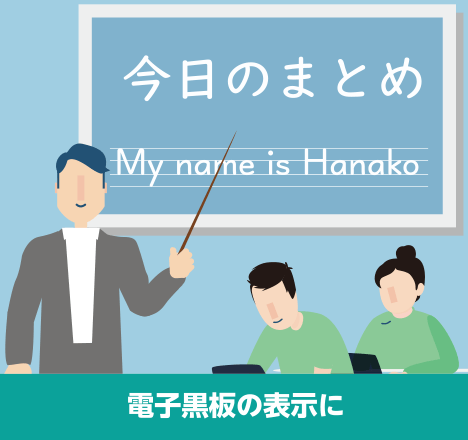
「MORISAWA BIZ+」は、教育現場のあらゆるドキュメントやコンテンツの作成に、多くの人々が利用しやすいユニバーサルデザイン(UD)フォントの利用を提案する新しいサービスです。
UDデジタル教科書体の特徴
一般的な教科書
筆書きの楷書に近く、線の太さに強弱があり見えにくい
ゴシック体
教育現場に準じた字形ではないため、運筆の方向がわかりにくく教えにくい
UDデジタル教科書体
ロービジョン(弱視)やディスレクシア(読み書き障害)に配慮したデザイン学習指導要領に準拠した字形。
電子黒板やタブレットの表示などICT教育で効果を発揮
より良い学びに適した字形に
- 運筆の向きがわかるように字形を工夫
- 同じ部首や同系列の構成要素を持つ漢字字形をルール化
MORISAWA BIZ+収録フォント
- 一般的なフォント
- BIZ UDフォント
文字のかたちが
わかりやすい
文字サイズが小さくても読みやすい
読みまちがえにくい
Office アプリケーションに最適化
MORISAWA BIZ+で
できること
読みやすいフォントだから
わかりやすさを
サポートします。
もし、文字が読みにくかったら・・・?
濁点と半濁点の判別が出来ない。
細い文字がかすれて読めない・・・。
それだけで学習意欲の欠如を引き起こしてしまうこともあります。文字の形が分かりやすく、読みやすく、読み間違えにくいフォントだから、わかりやすさをサポートします。
UDフォントで
コミュニケーションが
もっと快適に
広告費をかけずに塾や予備校を広めたい、大切な情報をもれなく保護者に伝えたい、「MORISAWA BIZ+」は、見やすくて分かりやすいフォントだから、伝えたい情報が伝わります。美しいフォントだからこそ、内製している文書やポスターの見栄えもバッチリ。
UDフォントで
学習塾業界のインクルーシブ教育※を実現
現在、通常学級には多様な子どもたちがともに学んでいます。文科省が実施した調査結果で「発達障害の可能性がある」とされた児童生徒の割合は6.5%でした。特別支援学校などに通っている発達障害やロービジョン(弱視)の児童生徒を含めると、さらに割合は大きくなります。
※障害の有無にかかわらず、すべての子どもを受け入れる教育
MORISAWA BIZ+は
こんなシーンでお使いいただけます
モリサワのUDフォントは
既にさまざまな場面で活躍しています
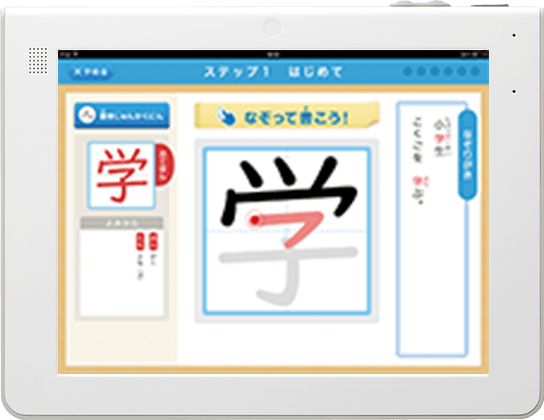
進研ゼミ 小学講座 小学生まるごと漢字アプリ
株式会社ベネッセコーポレーション 様
手書きの文字を自動判定し、小学生で習う漢字を学年を超えて正しい書き順・形で「書く力」を育むアプリです。小学1・2年生の漢字で採用されています。
ドラえもん はじめての論語
株式会社小学館 様
孔子の言葉にドラえもんのイラストが付いた小学生向きオールカラー論語入門書です。孔子の言葉部分に「UDデジタル教科書体」が採用されています。
藤子・F・不二雄(まんが原作)/安岡定子(著)
モリサワのUDフォントはユーザー評価に基づく
読みやすさのエビデンスを取得しています。
※モリサワUDフォントは、すべてUDフォントのエビデンスを取得していますが、
TrueTypeフォント化にあたり、一部デザインを調整しています。
ロービジョンのエビデンス
(UDデジタル教科書体の調査結果)
慶應義塾大学 中野泰志教授による
Aデジタルデバイス(タブレット)での見やすさの検証
縦組み(科目:国語)・横組み(科目:社会)で、UDデジタル教科書体と他社教科書体をタブレット画面で比較し、シェッフェの一対比較法を用いて、それぞれの見やすさを検証した。
いずれの評価においても「UDデジタル教科書体」が最も見やすい書体であった。
B紙に印刷したサンプルでの読みやすさの調査
日本全国の視覚支援学校に在籍している高校生42人へのアンケートとヒアリング調査、弱視教育に携わっている教員・専門家65人へのアンケート調査、全国の視覚支援学校で弱視の生徒を担当している教員104人へのアンケート調査を実施した。
弱視生徒にとっても教員からみても、弱視児童生徒の読書に「UD デジタル教科書体」がもっとも適した書体であった。
ディスレクシアの
エビデンス
(UDデジタル教科書体の調査結果)
大阪医科大学 LDセンター
奥村智人先生による
デジタルデバイス(タブレット)での見やすさの検証
読み書きに困難さがある26人の小学2~6年生を対象に、UDデジタル教科書体を含む4つの教科書体で縦組みと横組みの文章を制作し、一対比較法を用いた主観的読みやすさに関する検討が行われた。
縦組み横組みともに「UDデジタル教科書体」がもっとも読みやすい書体として子どもたちに選択された。
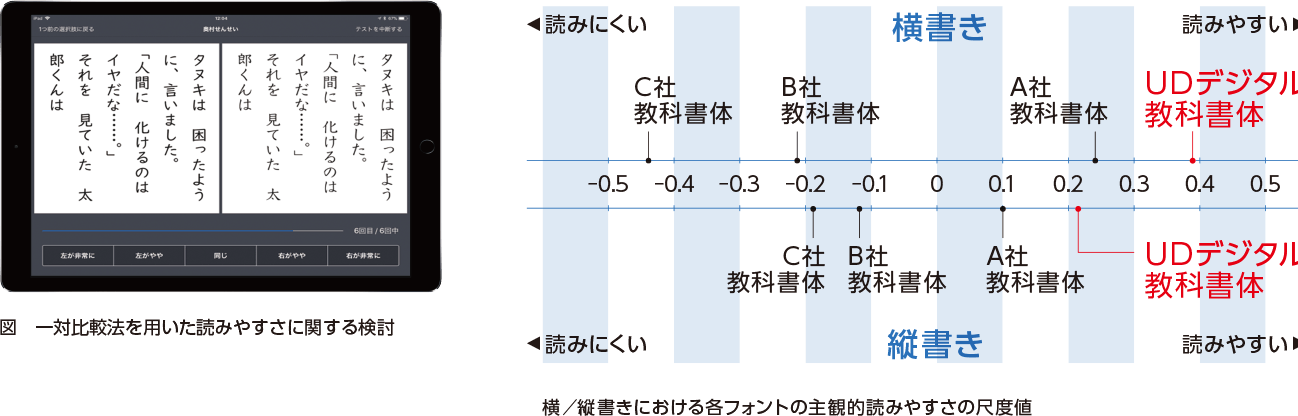
従来のビジネスフォントの比較調査
(BIZ UDゴシック・BIZ UD明朝の調査結果)
デジタルデバイス(タブレット)での見やすさの検証
全国93カ所のハローパソコン教室を対象に、UD書体の比較アンケート調査を実施。BIZ UDフォントと標準的なフォントの「見やすさ」を検証した。
ゴシック体・明朝体ともにBIZ UD フォントがもっとも見やすい書体として選択された。
見やすさの比較
BIZ UD新ゴ・BIZ UD新丸ゴ・BIZ UD黎ミンについて
BIZ UD新ゴ・BIZ UD新丸ゴ・BIZ UD黎ミンは、慶應義塾大学と共同で行った比較研究でその優位性が検証されたモリサワUDフォントをベースに作成されています。「必ず伝えたい情報」「注意を促したい文言」「さりげなく添えたい文章」など、必要な表現に合わせてフォントを変えることが可能となり、情報の「伝わりやすさ」に大きな差がつきます。数字の多い文書や提案資料、公的文書、各種案内など、より多くの人が目にする文書の作成に最適です。